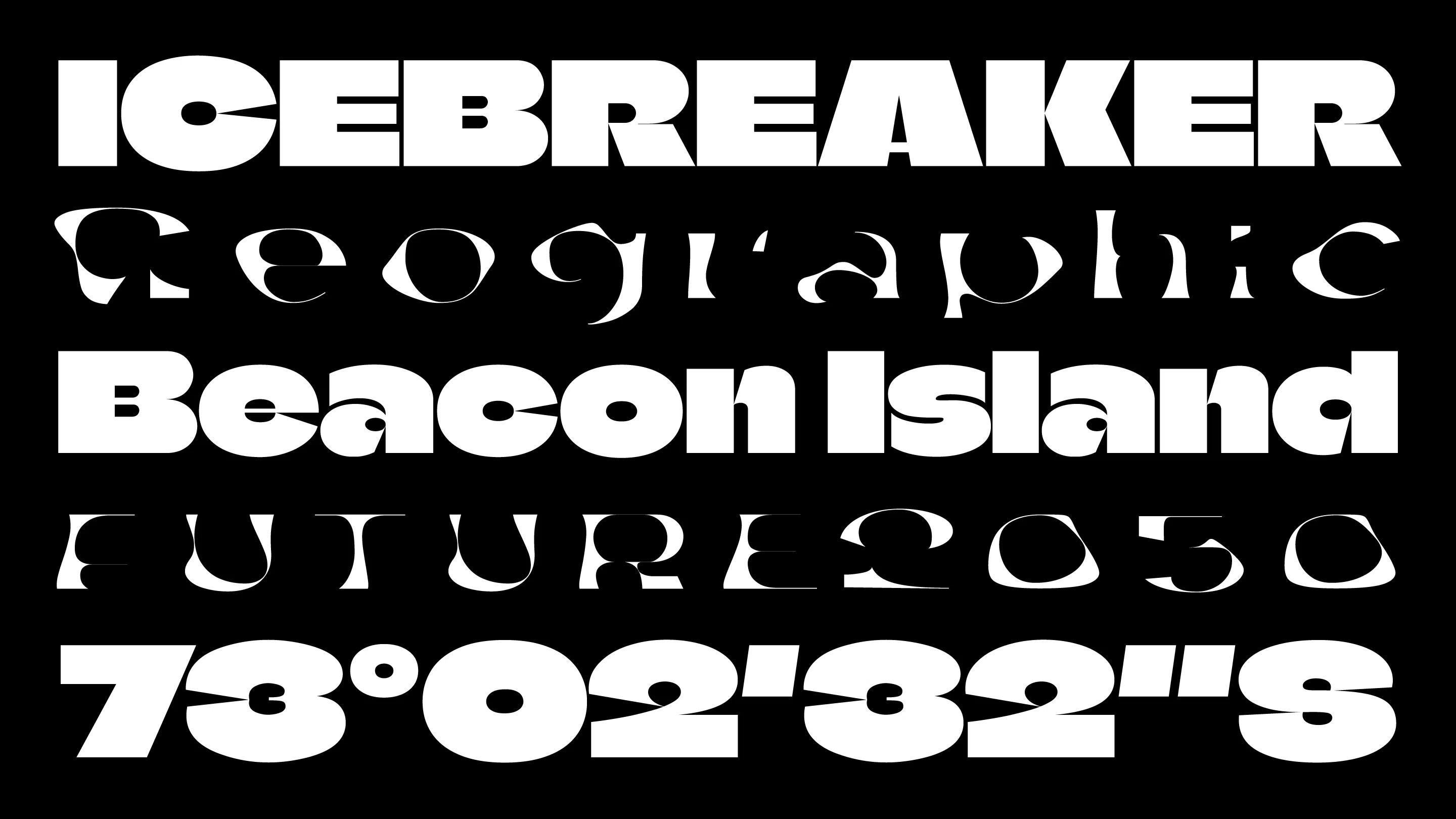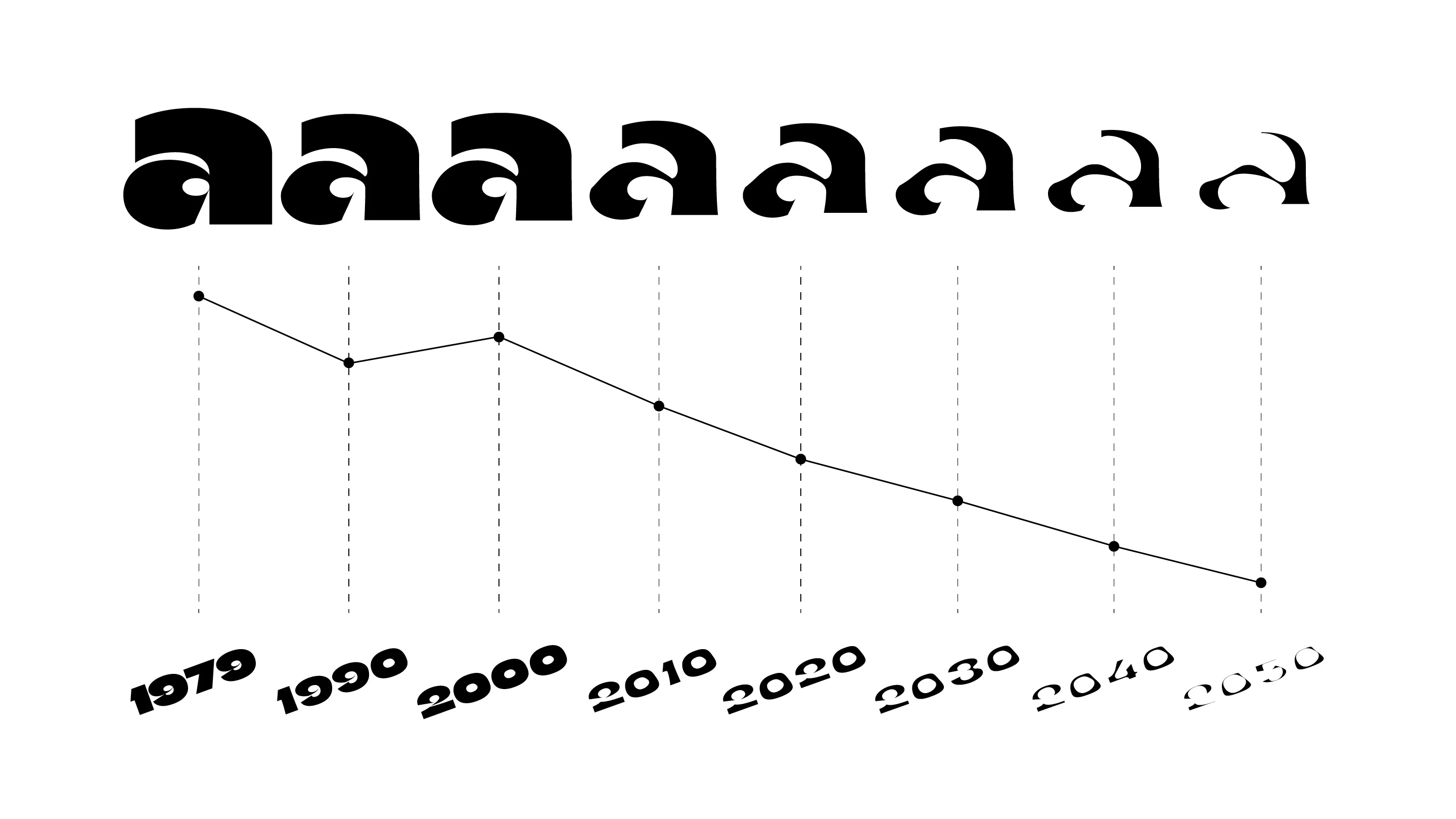
Helsingin Sanomat, Eino Korkala y Daniel Coull, 2021
The Climate Crisis Font es una tipografía variable cuyo eje de peso está vinculado a datos históricos y proyecciones futuras sobre el deshielo del Ártico. A medida que el usuario selecciona diferentes años, desde 1979 hasta 2050, el grosor del glifo disminuye, reflejando visualmente la pérdida de hielo.
Su principal aportación es la codificación de una narrativa sobre el cambio climático directamente en la morfología del glifo. Al vincular el tipo con datos científicos reales del Centro Nacional de Datos de Nieve y Hielo, la tipografía deja de ser un contenedor neutro de información para convertirse en la propia visualización de la crisis.
La relevancia de este proyecto reside en su uso innovador de la tipografía variable como una herramienta para la visualización de datos y la concienciación social. Es un ejemplo de cómo la tipografía puede comunicar un mensaje a dos niveles: a través del texto que se escribe y a través de su propia forma.
- Década: Década de 2020
- Función: Visualización de datos
- Contexto: Producto digital
- Grado de interactividad: Interacción débil o reactiva
- Input multimodal: No
- Tipo de input: Datos externos
- Tipo de output: Transformación morfológica
- Tecnología empleada: Tipografía variable
- Alfanumérica: Sí
- Mantiene codificación textual: Sí